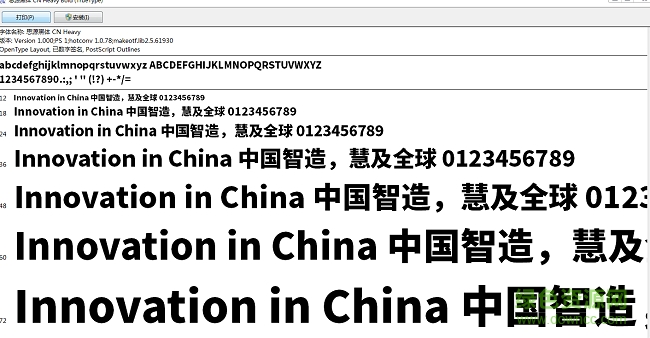
sourcehansanscnheavy字體是一款的思源黑體字體,字體本身看起來(lái)更簡(jiǎn)潔清晰,筆畫鮮明,造型規(guī)整,富于力度,視覺沖擊力強(qiáng)烈,適合作標(biāo)題和宣傳導(dǎo)語(yǔ),歡迎大家免費(fèi)下載!
【結(jié)構(gòu)的再設(shè)計(jì)】
結(jié)體的再設(shè)計(jì),是在傳統(tǒng)字體結(jié)構(gòu)基礎(chǔ)上,有所突破地打破原有字體結(jié)體規(guī)范,根據(jù)視覺形象的新型審美觀,將某些偏旁部手突破原有結(jié)構(gòu)的構(gòu)成規(guī)律,在原有的結(jié)構(gòu)編排上開創(chuàng)出新型的結(jié)構(gòu)。
【變化黑白區(qū)關(guān)系】
由字體筆畫構(gòu)成的實(shí)體稱作黑區(qū),與筆畫相依的虛體部分稱作白區(qū),黑白區(qū)的分界主要體現(xiàn)于實(shí)休筆畫與虛體非筆畫間的交界。
很多字體風(fēng)格的形成和變化,只是將這種分界線稍作移勸,就會(huì)形成截然不同的字體創(chuàng)意風(fēng)格。